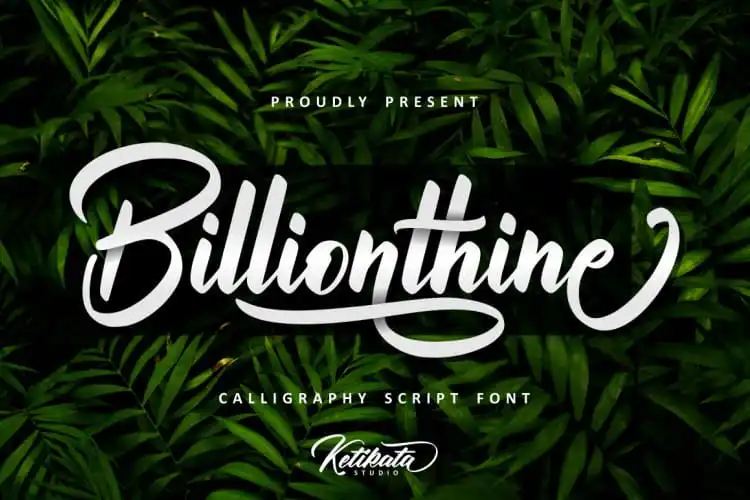
Billionthine Calligraphy Font – Fonte Grátis
Billionthine Calligraphy Font
Billionthine Calligraphy Font é uma opção perfeita para quem está procurando uma tipografia moderna que ressalta a elegância do estilo churrascado do calligrafia. Desenvolvida com cuidado por m@graphics, esta fonte vem equipada com alternativas estilizadas e swashes, permitindo que você personalize seus próprios designs de maneira única e eficaz. Suas linhas fortes e marcantes são perfeitas tanto para criar logotipos (ou Logotype), como para trabalhos diversos como cartões de visita, embalagens, materiais promocionais, tags de produtos ou qualquer outro projeto que precise de um estilo único e profissional. Este é o tipo certo quando você quer trazer uma pitada sofisticada e moderna a seus projetos. O Billionthine Calligraphy Font é uma escolha inteligente para quem procura estética elegante e funcionalidade inovadora, oferecendo flexibilidade e criatividade suficientes para adaptar o seu design à qualquer necessidade.